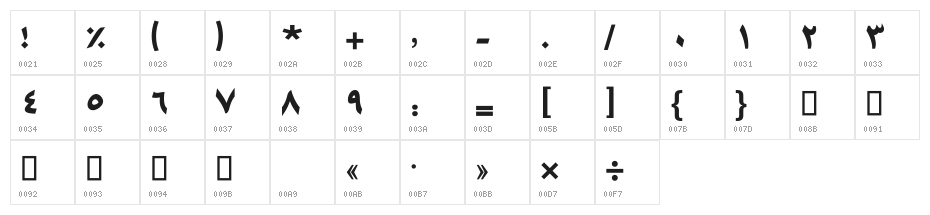
Lebanon Font
| Caso d'uso | Logos, Headlines |
| Progetti proposti | Ideal for creative projects such as posters, album covers, or branding that seeks to make a bold statement. |